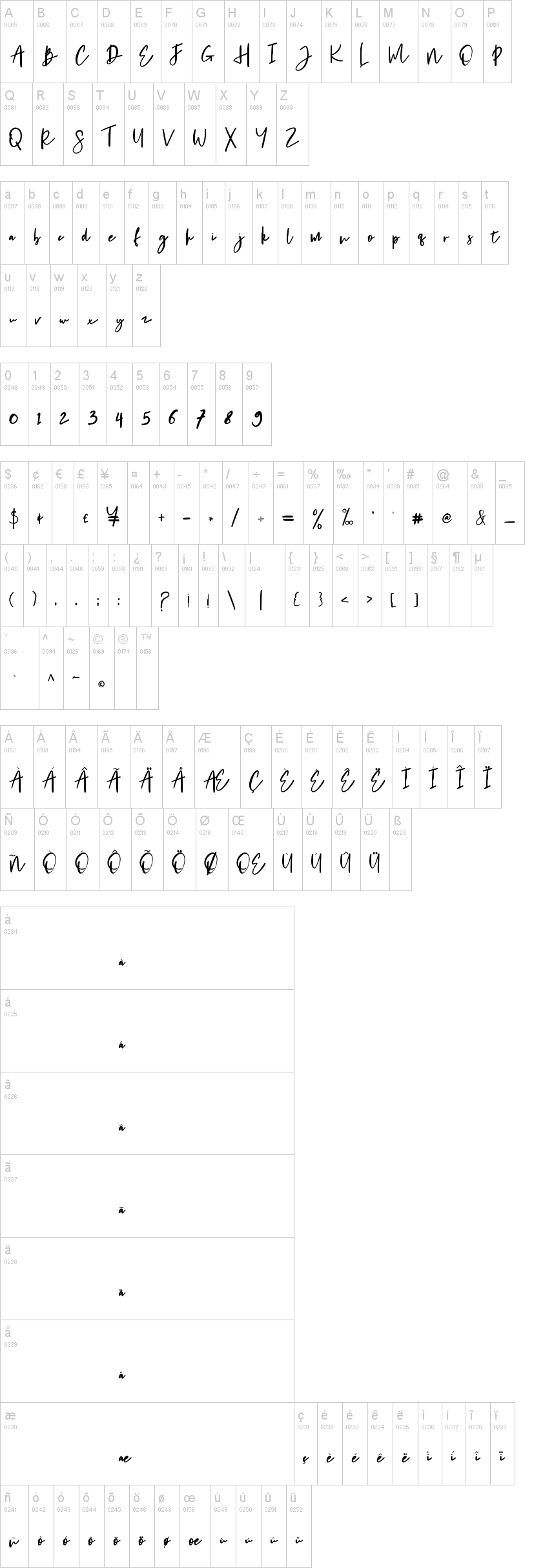
Chantelle
Chantelle 字体是由英国设计师John Stracke于1937年设计的一款英文字体。它具有精致的设计,优雅的线条,温柔的曲线,让人看起来更加精致大方。这款字体可以用于广告、标题、书籍封面、杂志封面、海报等,能够给人以优雅、温柔的感觉。
Chantelle是一款非常不错的手写艺术字体,具有很好的视觉感,适合于文化类的宣传设计、商业类品牌的广告和产品包装设计以及个性化文字排版等较多场景。
Chantelle字符映射图